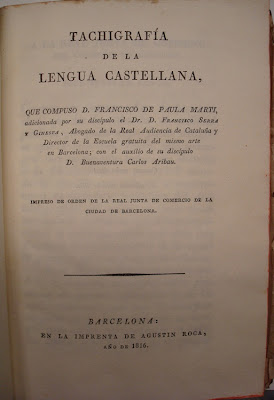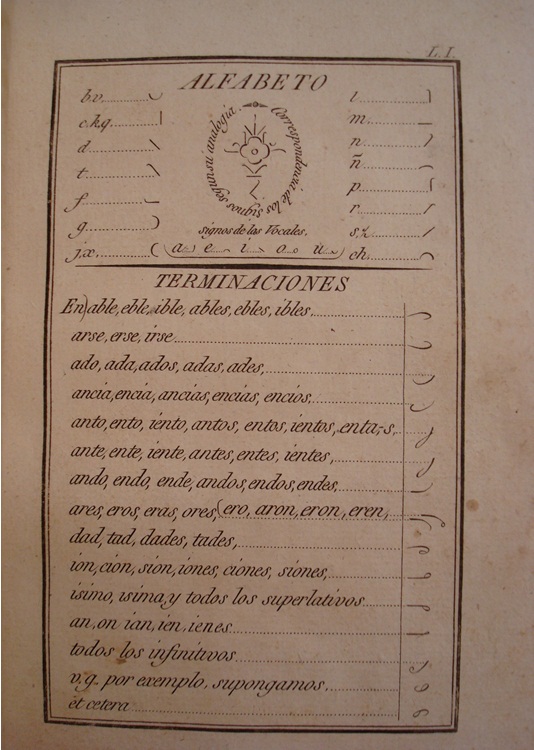
La obra del taquígrafo inglés S. Taylor: “Du Esay intendet to stablish a standart for an universal system of stenography, or short-hand writing” publicada en Londres el año 1786, se difundió muy rápidamente por Europa siendo traducida a diversos idiomas. Este será el punto de partida de la aventura taquigráfica en España.
F. de Paula Martí nace en Játiva el 1761, muere en Lisboa el 1824 y es considerado el padre de la taquigrafía española.
Martí Mora, Francisco de Paula. ESTENOGRAFÍA DEL ARTE DE ESCRIBIR ABREVIADO… Madrid: Imprenta de la Vega y Compañía, 1800. Primera edición.
8º. 18’5x11’5 cm. 1 folio en blanco, 31 páginas numeradas que incluyen el título, la portada y una portada secundaria + 11 láminas.
Esta obra fué la traducción y adaptación a la lengua castellana de la obra de Samuel Taylor “Du Esay intendet to stablish a standart for an universal system of stenography, or short-hand writing” publicada en Londres el año 1786. Este método fue muy popular y se editó varias veces en Inglaterra y en otros países como Francia, España y EEUU (Albany, 1810).
El mismo año, Paula y Martí publica una segunda edición en la que dedica algunas páginas a explicar las variaciones de su tratado respecto al de Samuel Taylor. Por este motivo, el 23 de abril, publica un articulo en el "El Diario" de Madrid: "Se da aviso a todos los que hayan tomado la Estenografía de Martí para que vayan a recoger la explicación, y a todos los que la tomen en adelante se les entregará con ella, sin alterar el primer precio de 16 reales de vellón cada ejemplar, en la Biblioteca de Castillo, frente a San Felipe el Real".
Alvarez Guerra, Juan. TAQUIGRAFÍA O MÉTODO DE ESCRIBIR con la ligereza que se habla ó se lee... Madrid: Imprenta Real, 1800. Primera edición. 8º. 24 páginas + 2 láminas + Exemplos de como escribir (24 páginas +15 láminas).
Álvarez Guerra nace en Zafra el 1789 y muere en Madrid el 1845.
Esta obra es también una traducción de la obra de Samuel Taylor antes mencionada pero de su edición en fancés.
La aparición de las dos obras a la vez causó en Madrid una grandiosa polémica sobre el método de escribir taquigrafía en castellano.
Aunque Paula y Martí saldrá victorioso de la contienda escribirá: "la Taquigrafía debe ser formada bajo los principios y la gramática de cada lengua" y decide "no publicar otro libro de Taquigrafía mientras no hubiese dotado a España de un arte propio y ajustado a las exigencias del mecanismo de nuestra lengua". Paula y Martí elaborará en 1803 el primer método propiamente español de taquigrafía castellana titulado “Taquigrafía Castellana o arte de escribir con tanta velocidad como se habla”.
Martí Mora, Francisco de Paula. TACHIGRAFIA CASTELLANA, ó ARTE DE ESCRIBIR con tanta velocidad como se habla, ... Madrid: imprenta sita de la calle de Capellanes, 1803. Primera edición.4º menor. 21x15 cm. Portada y XV páginas numeradas en romanos + 75 páginas +16 láminas + Suplemento a la Taquigrafía Castellana, (Madrid, 1804), 16 páginas + 4 láminas.
El año 1802 presentó Paula y Martí su trabajo en La Sociedad Económica Matritense y después de una buena acogida de la obra, se publicó el año siguiente. Este método de taquigrafía se utilizó para transcribir los discursos de las célebres Cortes de Cádiz de 1810.Esta obra se reditará tres veces más: los años 1813, 1821 y 1824.
Francisco de Paula y Martí será considerado el inventor de la taquigrafía castellana (*) y su influencia llegará hasta el s.XX. Otra invención de este gran erudito fue la pluma estilográfica.
| Portada |
Muestras:
Esquema de una pluma estilográfica
(*) En 1808, F. Paula Martí publicó también la obra: "Poligrafía, o Arte de escribir en cifra de diferentes modos, arreglado a los métodos de varios autores antiguos y modernos.- Con una colección de tintas simpáticas y comunes, el modo de hacer revivir la escritura en los manuscritos antiguos, y de borrar lo escrito cuando convenga, Por D. Francisco de Paula Martí, Catedrático de Taquigrafía" y en 1833 "Taquigrafía de la música, o arte de escribirla sin usar del pentagrama".
SERRA i GINESTA, FRANCISCO – (Martí Mora, Francisco de Paula)
"TACHIGRAFIA DE LA LENGUA CASTELLANA, que compuso D. Francisco de Paula Martí, adicionada de su discípulo el Doctor D. Francisco Serra y Ginesta, Abogado de la Real Audiencia de Cataluña y Director de la Escuela gratuita del mismo arte en Barcelona; con el auxilio de su discípulo D. Buenaventura Carlos Aribau"
Barcelona, Imprenta de Agustín Roca, 1816.